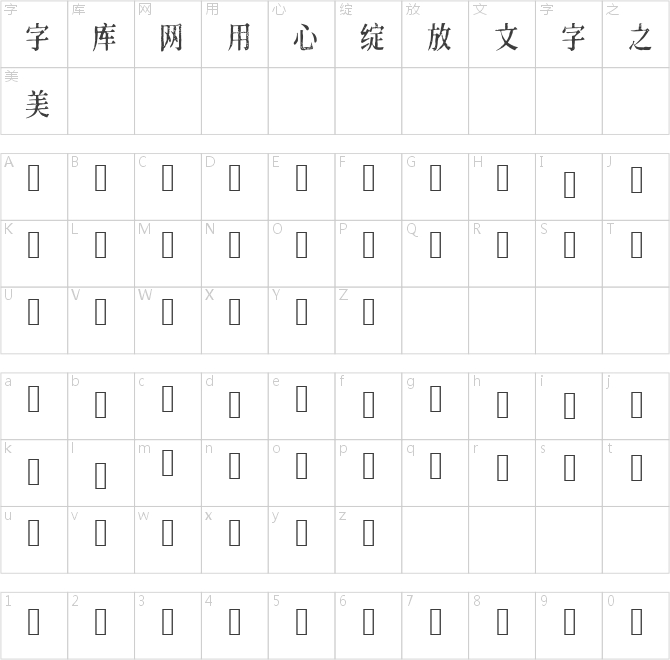
字體名稱: 令東齊伋體
令東齊伋體
• 修正了0.0.1版中的以下的字錯誤
• 字|宇、
令東齊伋體字體黃令東齊伋體QIJIFALLBACK字庫是一款讓人賞心悅目、百看不厭的中文字體,適合各類廣告和產品包裝設計應用,字體大小37.03MB,格式為ttf字體,上傳用戶是迷路的豬,作者/版權方為黃令東